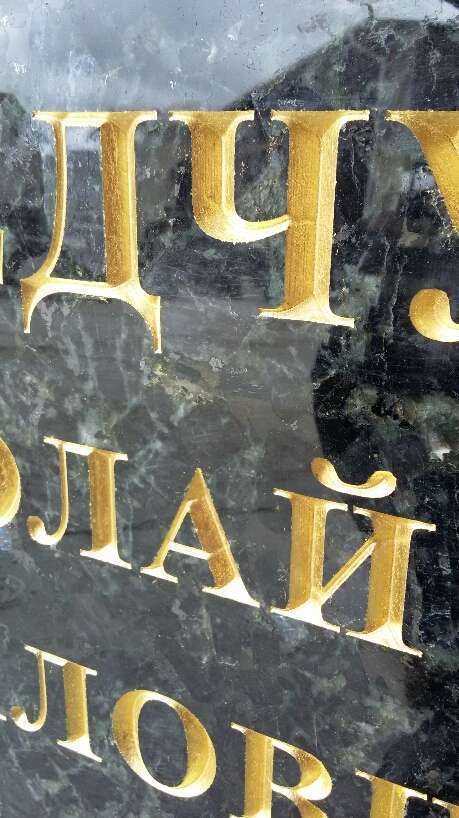
Никс Опубликовано 21 мая, 2025 Здравствуйте. Собираемся заказывать небольшой памятник, гранит светлый, буквы - глубокая рубка "на ус". Видел на форуме выкладывали пример, на фрезере сделанный текст такой же. Может ли кто-то подсказать контакты мастерских ( в СПб), кто делает на фрезере такое? Потому что в основном предлагают пескоструй, но он совершенно не годится. Подкупают гладкие внутренние грани, возможно ли добиться таких же ручной рубкой, а не на станке? Рассматриваем и фрезер и ручную рубку.
Денис Давыдов Опубликовано 21 мая, 2025 1 час назад, Никс сказал: возможно ли добиться таких же ручной рубкой, а не на станке? Возможно. Нужно найти только хорошего рубщика.